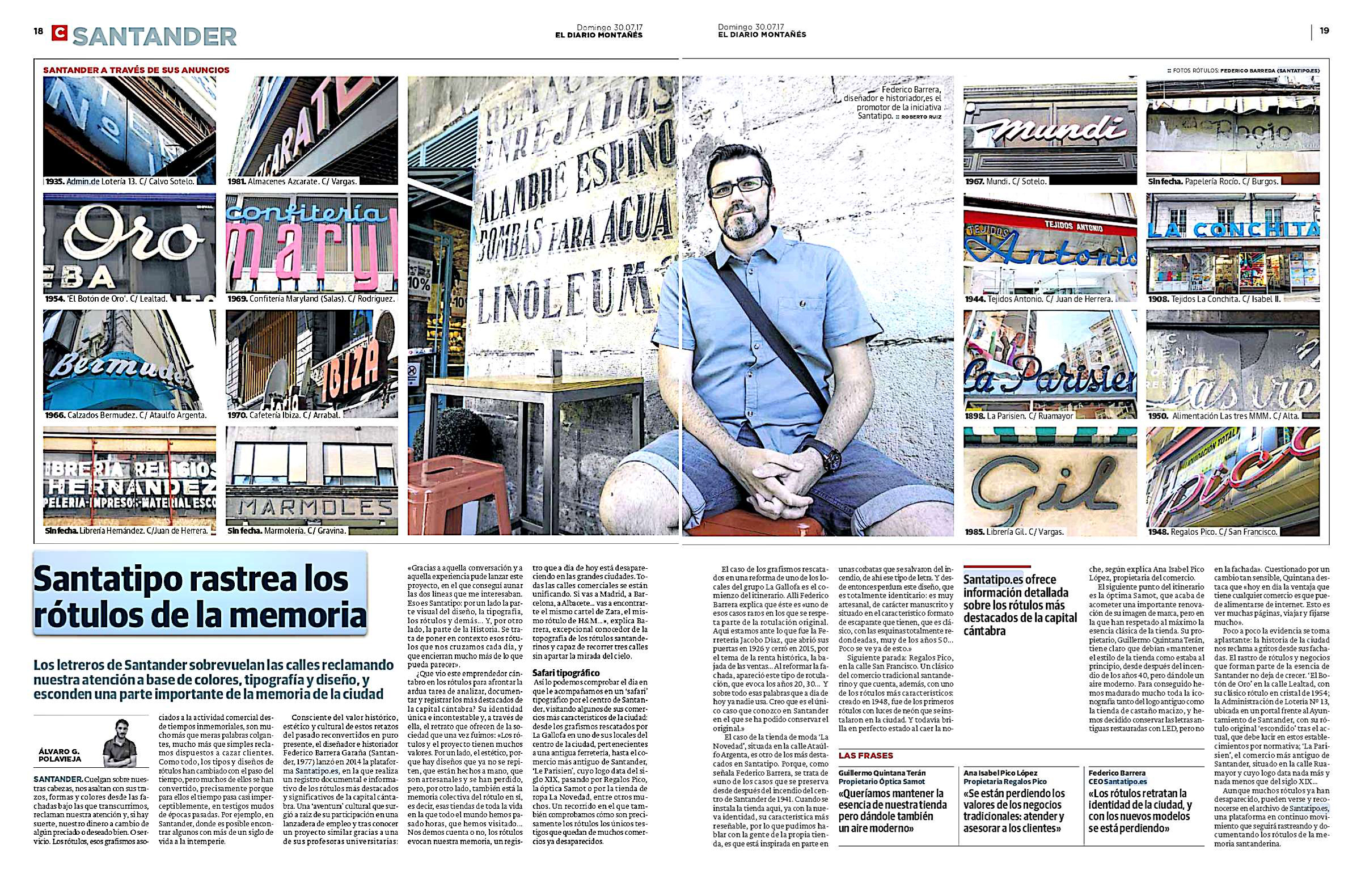
Reportaje: Santatipo rastrea los rótulos de la memoria
Un 20 de junio llegó a  la bandeja de entrada un mail que ponía «posible reportaje Santatipo».  A veces piensas que se puede tratar spam, como esos correos que ponen «optimizamos tu web», pero lo abrí por «si acaso». Y efectivamente, el cuerpo del correo no dejaba lugar a dudas. Se trataba de un mail de Álvaro Polavieja, periodista de El Diario Montañés, que se interesó por el proyecto. Más allá de esto, resaltar que me alegra enormemente poder compartir mi visión de las calles con todo el mundo a través de la web o las Redes Sociales. Pero nunca me había surgido la oportunidad de hacerlo con un medio de comunicación.
Lo primero que pensé fue: «¿y de qué voy hablar?», lo cierto es que el propio Álvaro con sus tablas me facilitó el camino entre cruces de mails. Y llegó el día. Quedamos en La Gallofa de Hernán Cortés, ahí iniciamos un paseo por el centro de la ciudad que se me antojó corto. Hay mucho que contar y poco tiempo. Quise destacar lo más curioso e interesante que se puede hoy observar, y claro, el hilo tiraba por otros sitios. El cuerpo te lo pide.
Un paseo tipográfico, es un paseo por la historia pasada y reciente de Santander a través de sus comercios. Hay muchos detalles que salen a la luz, hablas con las personas, aprendes. Por eso una mañana es corta, pero intensa. Cuando nos quisimos dar cuenta ya habían pasado más de tres horas y estábamos frente al precioso rótulo de cristal de «Las tres M«. Ahí terminamos el paseo.
Paso el tiempo y el 30 de julio salió por fin el reportaje en papel y el 31 en la web, con video y todo. Una locura (positiva) lo que ha supuesto. De todo me quedo con lo más importante, y es que por fin se ha dado a conocer uno de lo miles de pequeños proyectos que mucha gente hacemos por España para salvaguardar la memoria de nuestras calles, y poner en valor un elemento tan icónico como son los rótulos. Y por último, dar las gracias a Álvaro Polavieja por la oportunidad